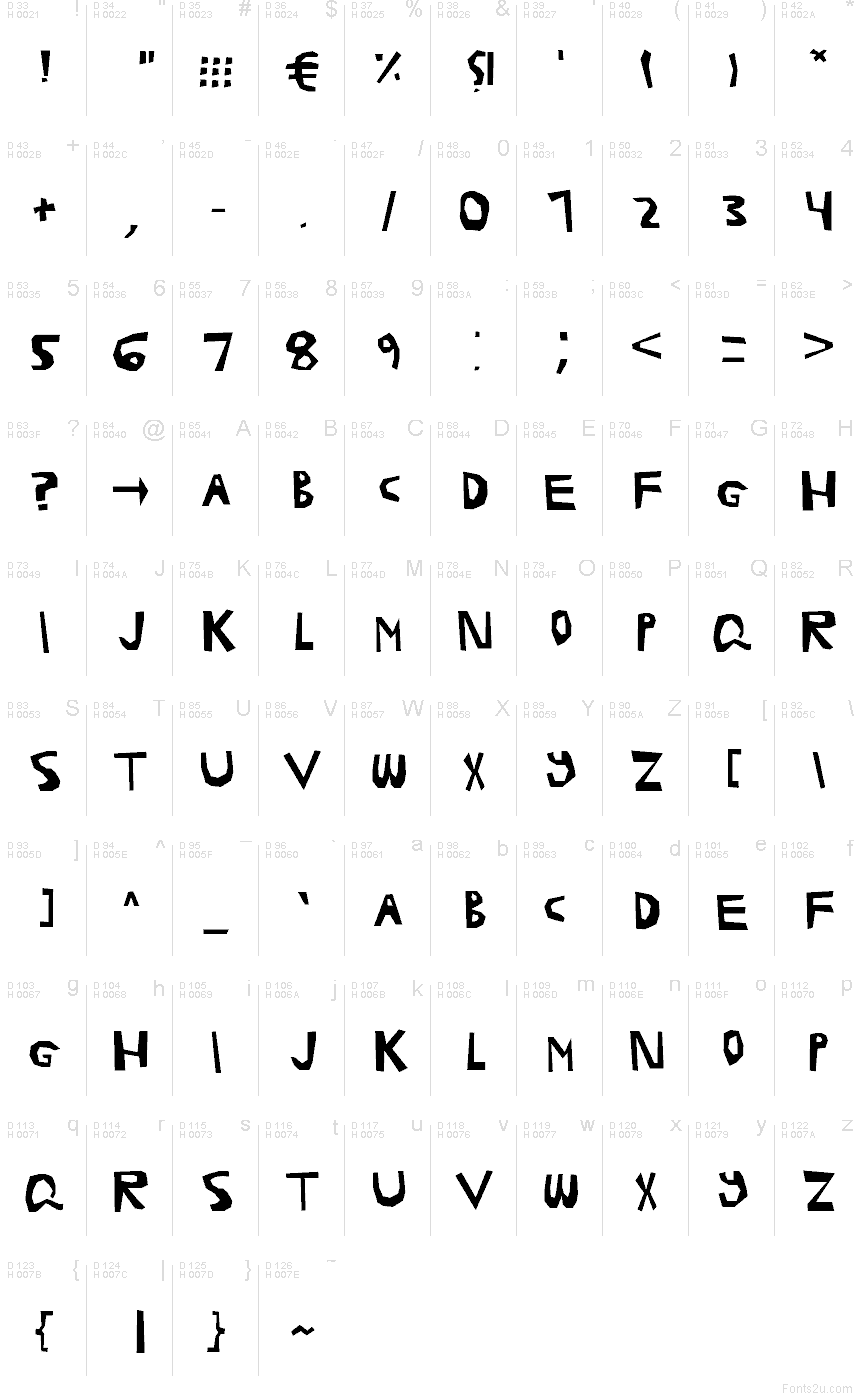
AJ
AJ, ein Werk von Silly Stella (LegendaryTypo), ist eine kostenlose kantige Display-Schrift in Großbuchstaben mit einer stumpfen, papierartigen Anmutung. Die Buchstaben wirken fett und reduziert, doch der scharfe Fuß beim J und die eingekerbten Verbindungen im A verleihen der Schrift einen leicht schrägen Rhythmus, der sie alles andere als gewöhnlich macht.
Sie eignet sich perfekt für Plakatüberschriften, Zine-Cover, Titelkarten für Spiele, Band-Logos und kurze Verpackungsdesigns – überall dort, wo eine kostenlose Schrift mit markanter Silhouette mehr Wirkung mit weniger Zeichen erzielen soll. Setzen Sie sie ein, wenn Sie kompakte Wörter, Monogramme oder ausdrucksstarke Initialen suchen, die grafisch und ein wenig frech wirken sollen, statt neutral.